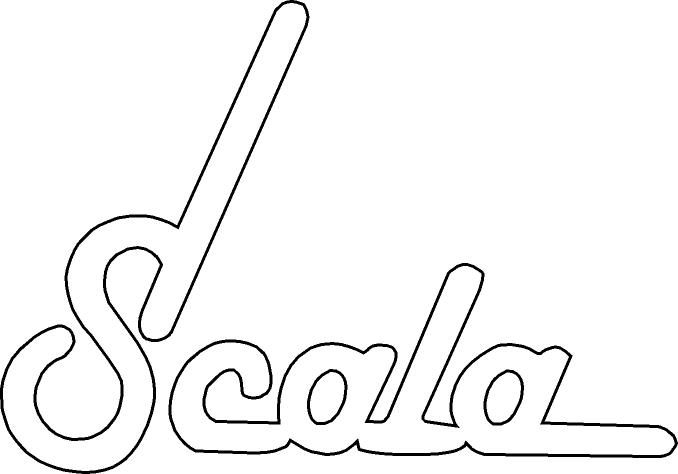
Ich würde mal sagen, da ist an allen Buchstaben rtwas herungebastelt worden, dann ist irgendwann das Original verloren gegangen, und man hat es dann gescannt und getraced, was zu diesen unsauberen Konturen geführt hat.